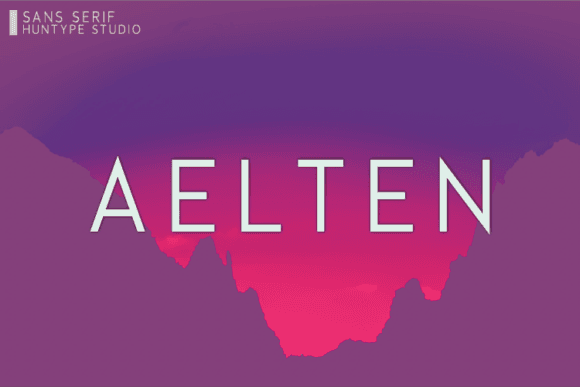
Fonte Aelten para Cricut, Silhouette e designs para impressão.
Esta é uma fonte manuscrita encantadora, feita sob medida para artesãos e criadores que usam máquinas de corte ou formatos de impressão. Aelten apresenta traços limpos e um toque orgânico, perfeitos para adicionar calor e elegância a qualquer projeto.
Como fonte, Aelten traz personalidade e flexibilidade para uma ampla gama de aplicações. De adesivos de vinil a impressões digitais, ela se integra perfeitamente tanto a projetos casuais quanto profissionais.
Otimizado para corte e impressão, oferece desempenho confiável em softwares Cricut, Silhouette e de design, com limpeza mínima necessária.
Para quem é indicado?
- Artesãos e designers de projetos "faça você mesmo"
- Usuários das máquinas Cricut e Silhouette
- Criadores de artigos de papelaria e convites
- Professores, pais e entusiastas
- Designers de produtos para impressão
O que você pode fazer
- Arte de parede e cartões de felicitação para imprimir
- Adesivos de vinil para canecas, copos térmicos e presentes.
- Placas, menus e convites para casamentos
- Etiquetas, planejadores e adesivos
- Designs personalizados de roupas e sacolas ecológicas
Por que você vai adorar
- Traços manuscritos elegantes com ótima fluidez.
- Ideal tanto para corte quanto para impressão.
- Totalmente compatível com Cricut e Silhouette.
- Ideal para looks formais e casuais.
P: Que tipo de fonte é Aelten?
A: Aelten é uma fonte manuscrita suave, criada para trabalhos manuais, materiais impressos e design digital.
P: Ele solda bem em projetos com a Cricut?
A: Sim, o Aelten foi projetado para soldagem limpa, sendo ideal para recortes em vinil e papel.
P: Pode ser usado para convites de casamento?
A: Sem dúvida. O design elegante da fonte Aelten a torna perfeita para artigos de papelaria formais e convites.
| Recurso | Fonte Aelten | Roteiro Genérico A | Caligrafia Genérica B |
| Estilo da fonte | escrita à mão | Escrita cursiva formal | Estilo manuscrito casual |
| Compatibilidade da máquina | Compatível com Cricut e Silhouette | Pode exigir ajustes. | Não otimizado para corte |
| Uso recomendado | Artesanato, sinalização, convites | Design de impressão formal | Diário digital |